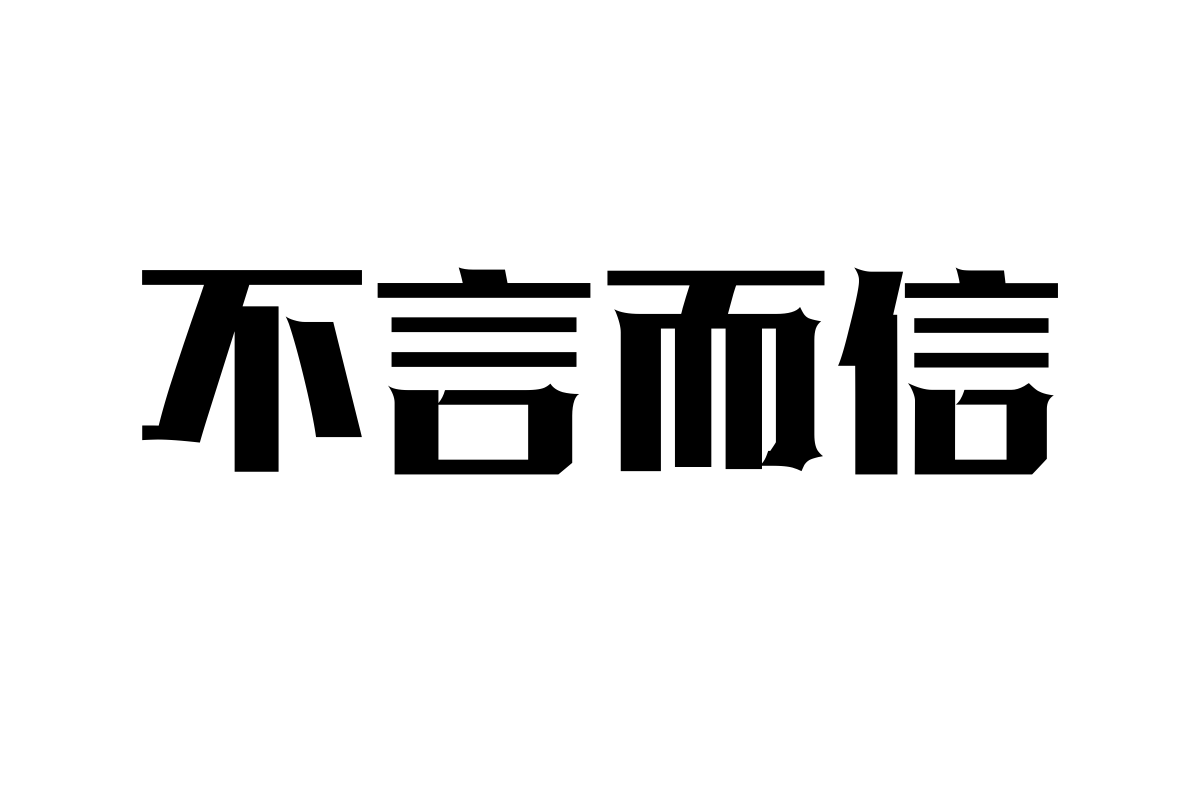
上首星斗体是一种汉字字体,由北京华文字库有限公司开发。这种字体具有独特的风格和特点,包括:
1. 字形独特:上首星斗体的字形独特,笔画流畅,结构紧凑,给人一种简洁、明快的感觉。
2. 字体美观:上首星斗体的字体美观大方,适合用于各种场合的书写和设计。
3. 易于识别:上首星斗体的字形易于识别,无论是手写还是印刷,都能保持清晰可辨。
4. 适用范围广:上首星斗体适用于各种场合的书写和设计,如广告、宣传、报纸、杂志等。
总之,上首星斗体是一种独特而美观的汉字字体,适合用于各种场合的书写和设计。